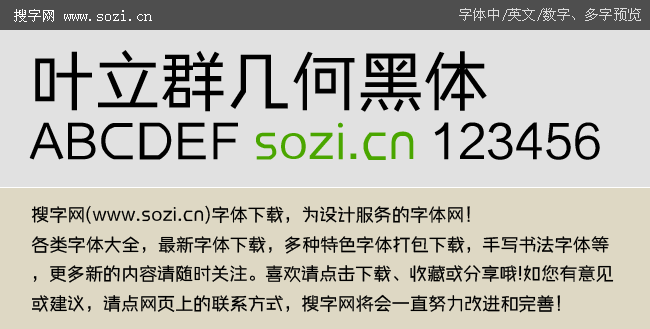
葉立群幾何黑體
搜字網(wǎng)提供一款葉立群幾何黑體中文字體下載,葉立群幾何體是一款以黑體為原形設(shè)計(jì)的中文藝術(shù)字體,字體簡(jiǎn)潔漂亮,效果非常出色,適合應(yīng)用于廣告設(shè)計(jì)、名片設(shè)計(jì)、包裝印刷、產(chǎn)品設(shè)計(jì)等應(yīng)用。